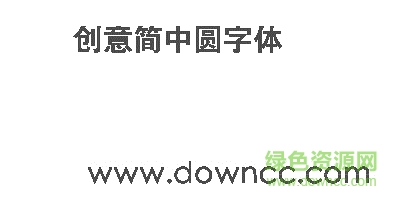
創(chuàng)意簡(jiǎn)中圓字體是一款端正大氣的創(chuàng)藝字體,筆畫粗壯,平整順滑,看上去非常美觀,使用字體后會(huì)讓你的字形看上去大氣美觀,喜歡就來綠色資源網(wǎng)下載吧!
美工設(shè)計(jì)方面的字體,該字體渾厚高古,勁健雄奇,意態(tài)跌宕,蒼勁峻逸,看上去十分美觀,整體效果非常統(tǒng)一,且字庫完整,可以廣泛應(yīng)用于廣告設(shè)計(jì)、包裝印刷、海報(bào)、ppt、影視制作以及內(nèi)容用字等領(lǐng)域,